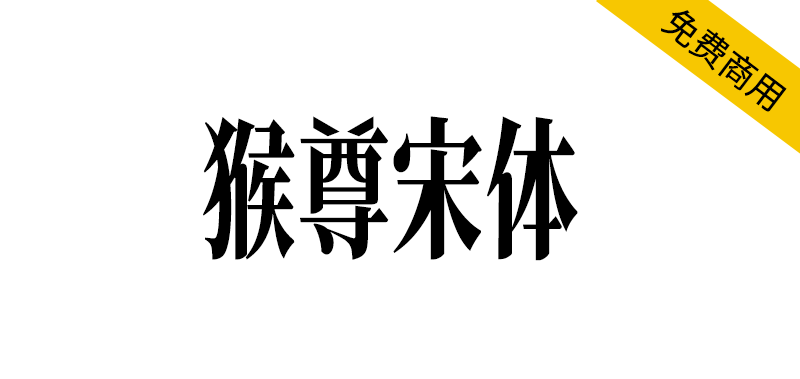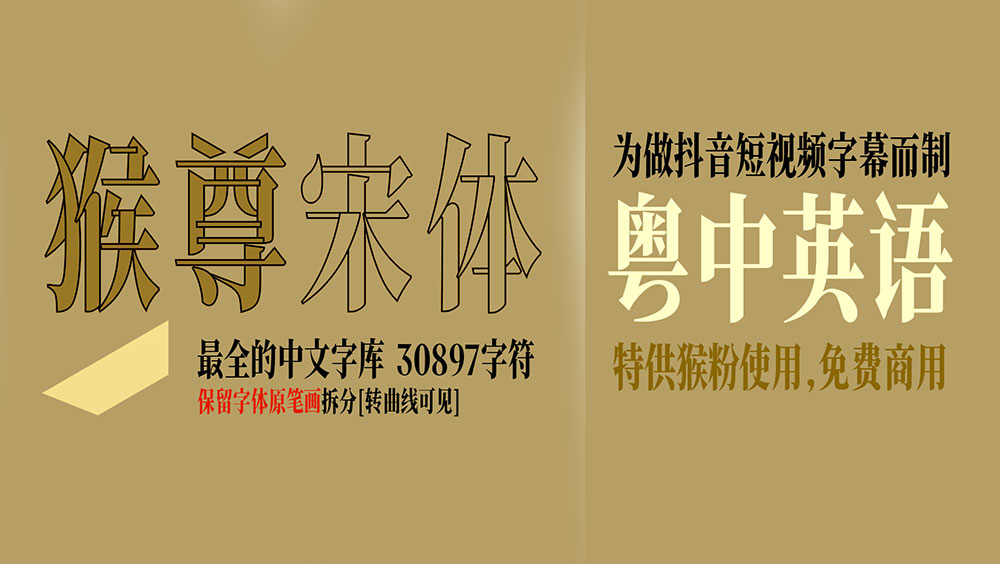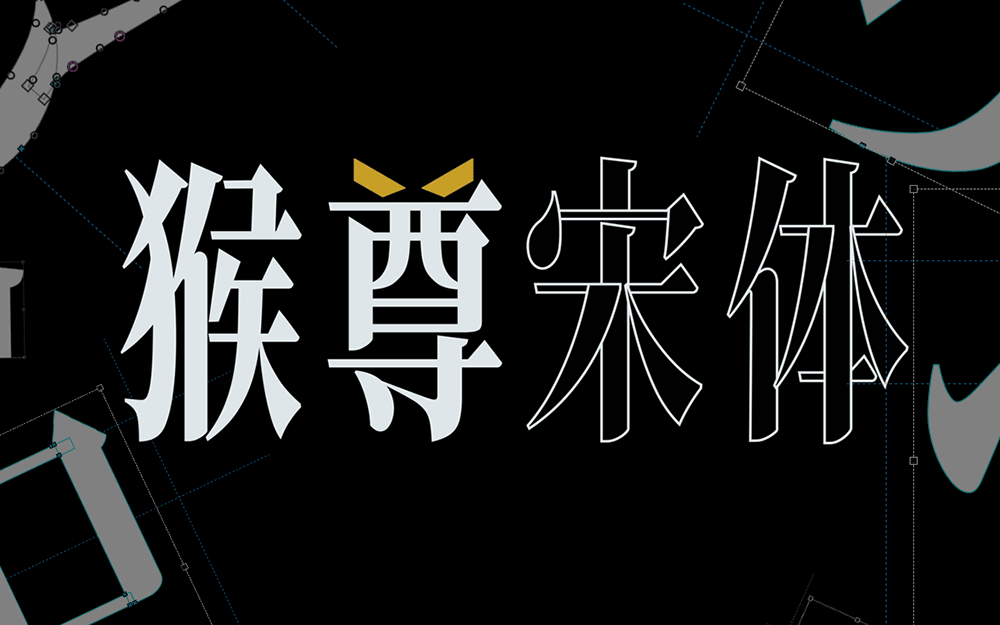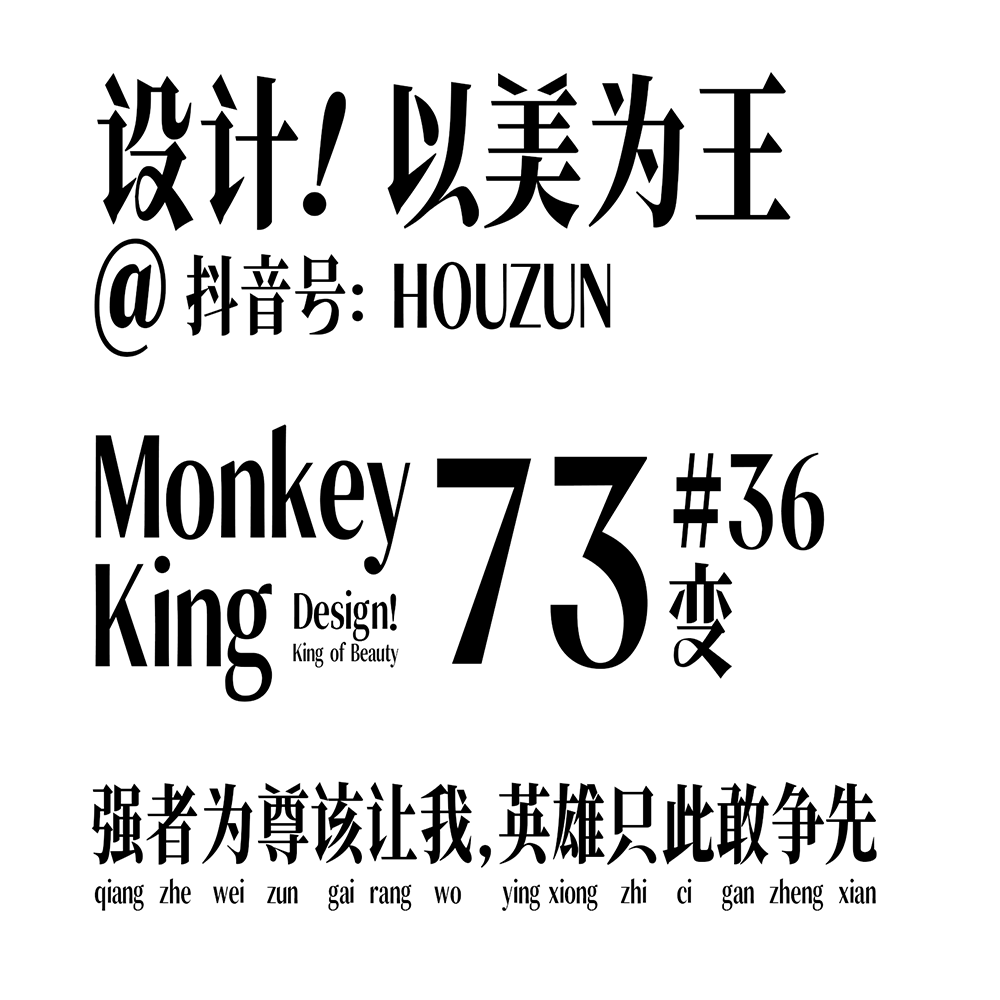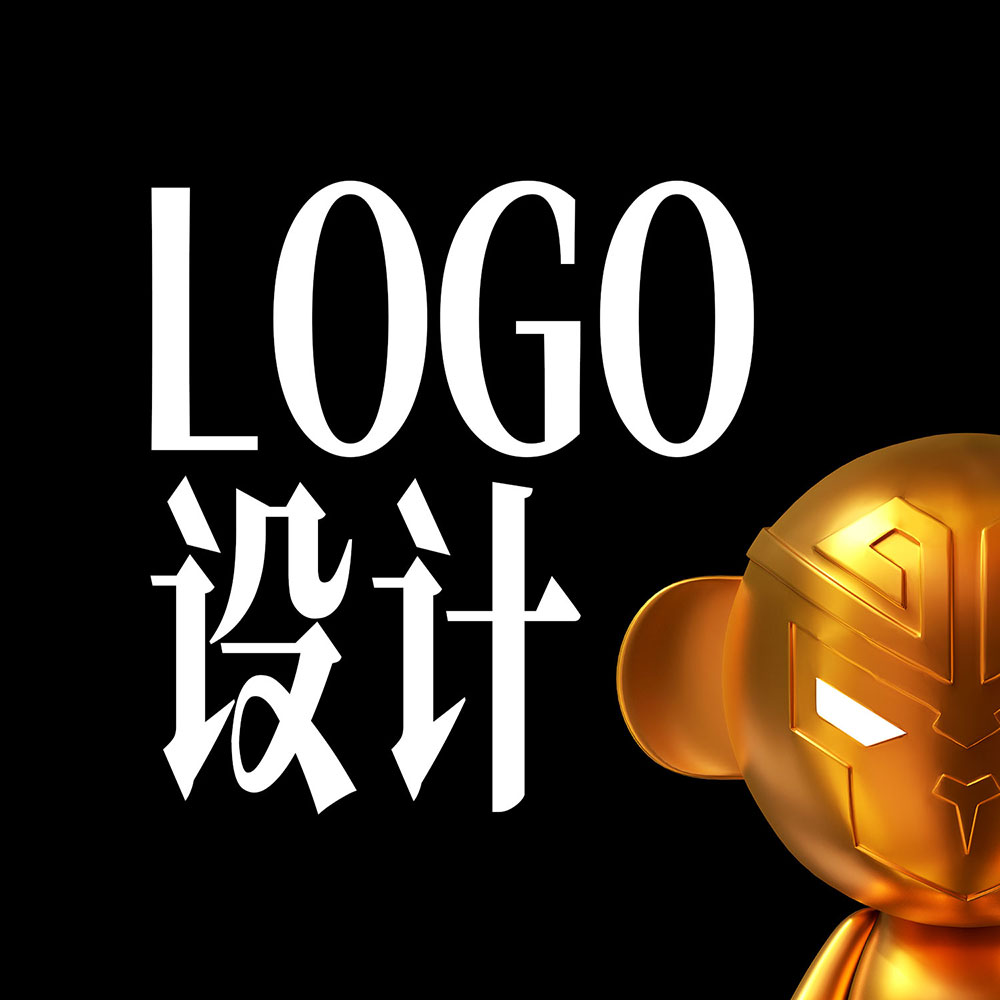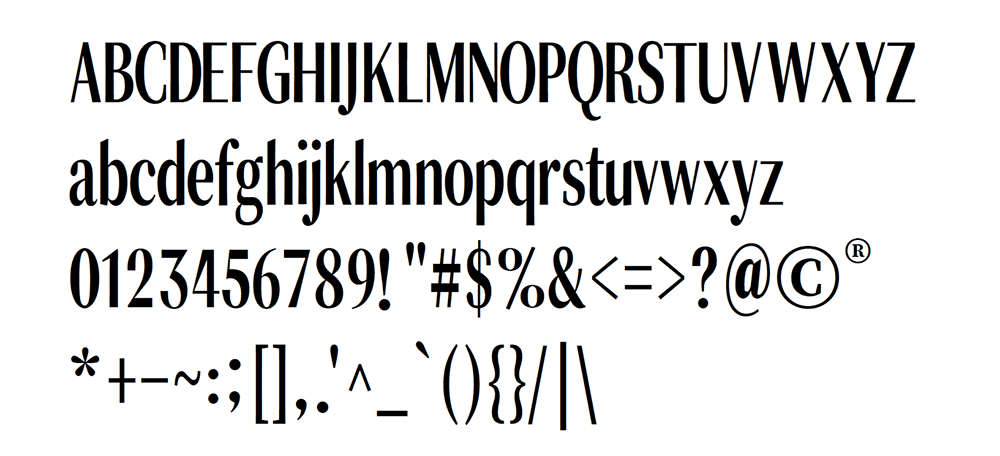
猴尊宋体是由抖音设计博主猴尊提供的一款免费商用字体,基于思源字体的比例更改为黄金比例值,字体保留书写每笔的原笔画,即文字笔画在illustrator里的创建轮廓、CoreIDRAW里的转为曲线,可编辑或移动构成字体的每个独立笔画,便于对字体的二次创作。部分字体笔画、字母、数字、符号等字体重构设计,为短视频的手机竖屏阅读时,一行文字可放下更多(更大)的字,用于大标题时,依具精致感。字体保留原笔画不合并(转曲线后可见,你可随意继续创新),个别笔画加入书法手写的笔画感觉,字体有种独特高雅的高级感!